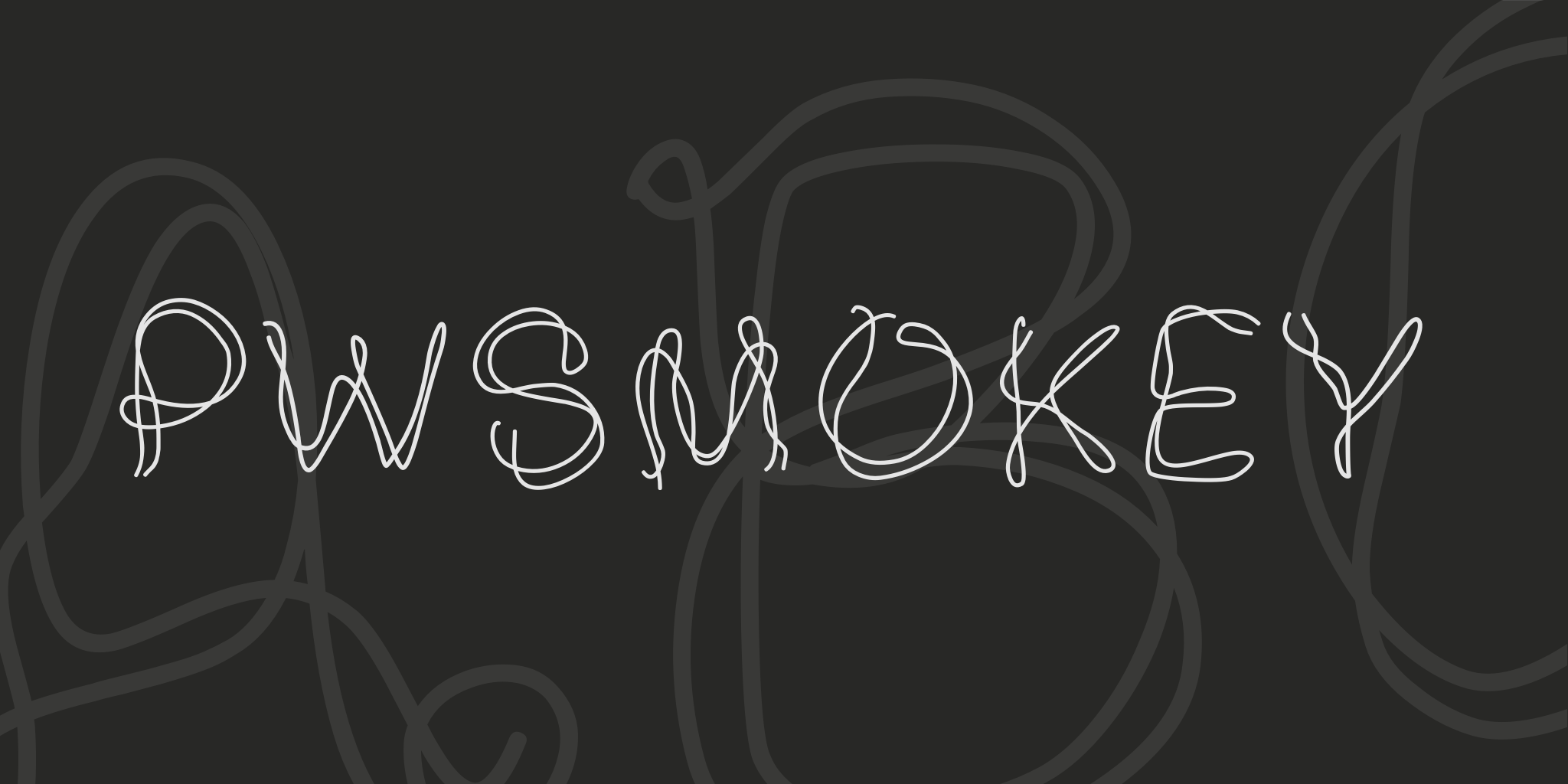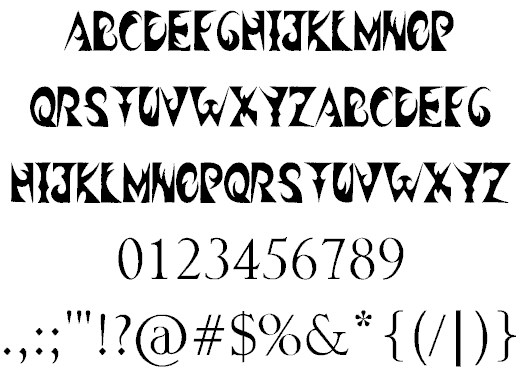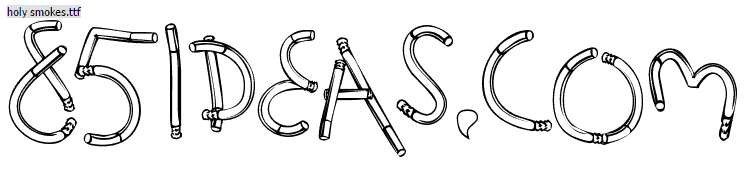
12+ der besten kostenlosen Smoke-Schriftarten für Designer 2021
Veröffentlicht: 2015-12-18Designer sollten sich darauf einstellen, diese Rauchschriftarten in ihren nächsten kreativen Grafikdesignprojekten wie Websites, Logos, Flyern, Postern und vielem mehr zu verwenden. Eines der wichtigsten Dinge, die Sie tun sollten, ist, sich auf die Anzahl der Websites mit den besten kostenlosen Smoke-Fonts zu konzentrieren. Wir haben für jedes Designprojekt eine Liste mit über 12 kostenlosen Smoke-Fonts zusammengestellt. Wir haben dies getan, um Ihre Mühe und Zeit zu sparen. Einige der kostenlosen Smoke-Fonts in dieser Liste können kostenlos heruntergeladen werden, während andere kostenpflichtig sind. Sie müssen nur eine kleine Spende leisten, um die kostenlosen Smoke-Fonts kommerziell nutzen zu dürfen. Wir sind zuversichtlich, dass Ihnen auch die besten kostenlosen arabischen Schriftarten gefallen werden.
Schriftarten mit rauchigen Effekten werden nie aus der Mode kommen, sie wurden immer wieder von Designern verwendet, um ihren Projekten Pep zu verleihen. Rauchschriftarten sind interessant und haben eine gewisse Kühnheit, die Menschen zum Text hinzieht. Egal wie attraktiv die anderen Elemente sind, diese Rauchschriftarten werden die Aufmerksamkeit des Betrachters auf den gewünschten Bereich lenken. Diese Schriftarten verleihen dem Inhalt die dringend benötigte Einzigartigkeit und helfen Ihnen, die Vielfalt Ihrer Designs zu präsentieren, insbesondere wenn sie mit Beautiful Winter and Christmas Wallpaper For Your Desktop integriert sind.
Warum die besten kostenlosen Smoke-Fonts verwenden
Im Laufe der Jahre haben Designer Rauchschriften in ihren Projekten verwendet, um ihnen ein attraktives und mutiges Aussehen zu verleihen. Die kostenlosen Smoke-Fonts wurden in den Dark-Design-Projekten ausgiebig genutzt. Unabhängig davon, ob das Design starke visuelle Grafiken enthält, erleichtern Rauchschriften es Ihnen, Ihre Botschaft an Ihr gesamtes Publikum weiterzugeben. Sind Sie ein kreativer Designer, der nach dem besten Weg sucht, beeindruckende Produkte zu bauen, suchen Sie nicht mehr! Die Rauchschrift lässt Ihren Text und Ihre Titel fetter und einzigartiger aussehen. Sie können diese auch in die besten kostenlosen Cowboy-Schriftarten für das Design von Westerntiteln integrieren.
Smoke Fonts können in Titeln, Überschriften, Logos, Postern, T-Shirts, Grafikdesign, Websites, Print und in persönlichen Projekten verwendet werden. Für einen Designer ist es schwierig, unter den vielen im Internet verfügbaren Schriftarten eine gute Smoke-Schriftart zu finden, insbesondere wenn sie nach einer kostenlosen Schriftart suchen. Ich habe versucht, ihre Aufgabe zu erleichtern, indem ich eine Liste mit über 12 kostenlosen Smoke-Fonts für Designer zusammengestellt habe. Einige der Schriftarten sind nur für den persönlichen Gebrauch kostenlos. Bitte überprüfen Sie die Lizenzvereinbarung, bevor Sie eine der Smoke-Schriftarten in Ihrem kommerziellen Projekt verwenden.
Verdampfte BB-Smoke-Schriftart
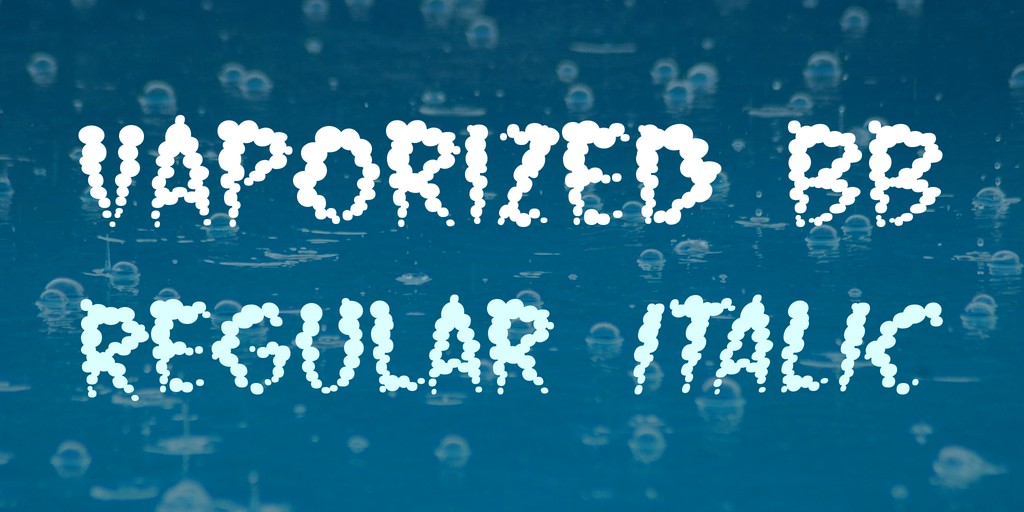
Vaporized BB Font wurde von Nate Piekos entworfen, die Rauchschrift ist wunderschön und in normaler und kursiver Schrift erhältlich. Die Buchstaben wirken verzerrt und verzerrt, die rauchende Schrift kommt auch mit Soundeffekten daher. Die Schriftart eignet sich hervorragend für jedes Projekt, das Rauch- oder Wolkeneffekte und knisternde Energiestrahlen erfordert.
Pucha-Rauch-Telegraph
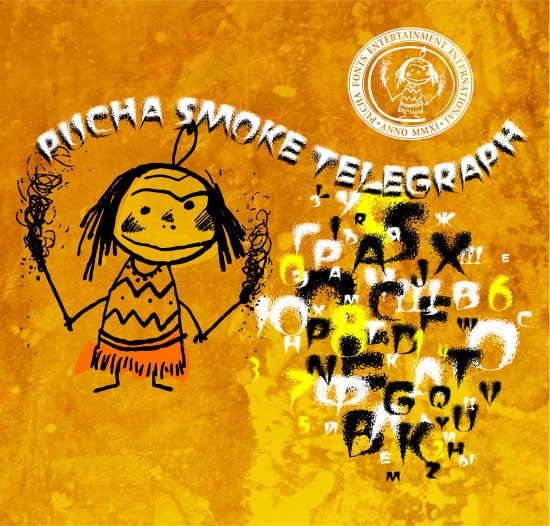
Die Schriftart Pucha Smoke Telegraph ist ziemlich fett und wird die Aufmerksamkeit des Lesers sofort auf den Text lenken. Diese Schriftart kann verwendet werden, wenn Sie eine starke Botschaft vermitteln möchten. Der Schriftsatz enthält Großbuchstaben, Kleinbuchstaben, gängige Symbole und Zahlen. Die Rauchschrift ist sowohl für den persönlichen als auch für den kommerziellen Gebrauch verfügbar. Es geht Hand in Hand mit den Free Asphalt Textures for Designers.
Alpha-Rauch
Alpha Smoke ist eine lustige Rauchschrift mit einem Rauchwolkeneffekt auf allen Alphabeten. Es ist eine coole rauchende Schriftart, mit der Sie Ihre Botschaft anzeigen können. Sie kann auch auf Postern, Websites oder praktisch überall verwendet werden, wo Sie möchten. Der Schriftsatz umfasst Großbuchstaben, Kleinbuchstaben, einige Symbole und Zahlen.
Alte Träume Schriftart
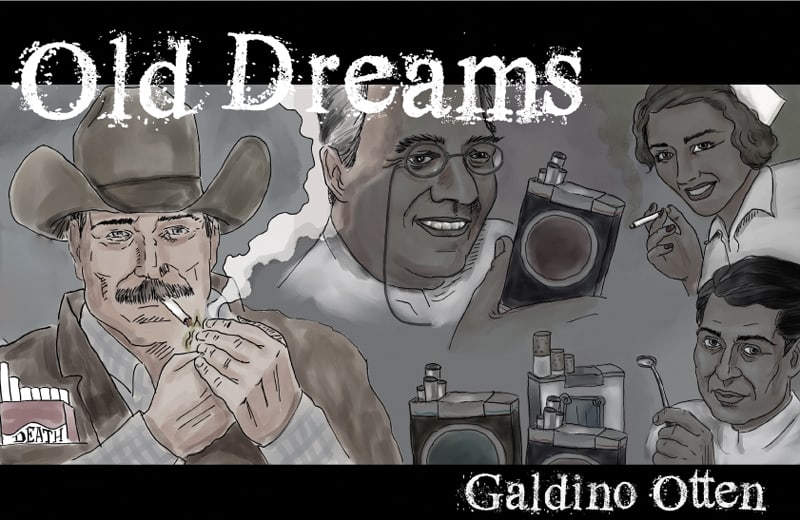
Old Dreams Font wurde von Galdino Otten entworfen; es ist eine serifenrauchende schrift mit staubigem effekt. Die Buchstaben und Symbole der Schriftart haben einen Grunge- und Sand-Look. Die Schriftart ist ideal für Schlagzeilen, Druck, Poster oder jedes Ihrer Designprojekte. Die Rauchschrift ist für den persönlichen Gebrauch kostenlos; es enthält Großbuchstaben, Kleinbuchstaben, Symbole und Zahlen.
Nach Cheret Schriftart
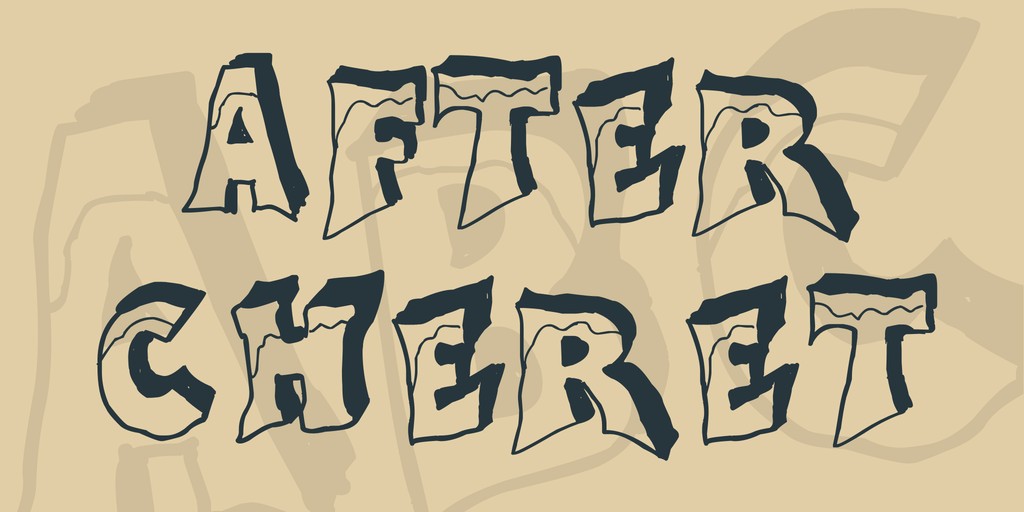
Nachdem Cheret Font eine weitere brillante Rauchschrift von Galdino Otten ist, ist es eine wunderschöne Schriftart mit klobigen Buchstaben und etwas, das wie Eis auf jedem Buchstaben oder Zeichen aussieht. Es ist eine 3D-Schriftart und hebt sich von den anderen ab. Sie kann verwendet werden, um einen bestimmten Bereich Ihres Designs, Inhalts oder Drucks hervorzuheben. Sie können diese Schriftart für Ihre persönlichen Projekte verwenden.
Tabaquera-Schriftart
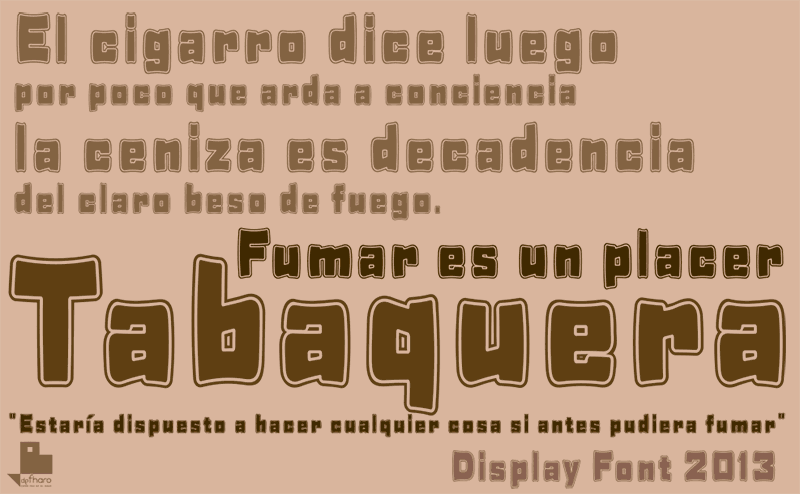
Die Tabaquera-Schrift wurde von Fernando Haro entworfen; die rauchende schrift ist eine schön konturierte, klobige, quadratische schrift mit abgerundeten ecken. Es ist eine einzigartige Rauchschrift, die jedem Ihrer Design- oder Webprojekte einen Hauch von Skurrilität und Stil verleiht. Die Schriftart Rauch hat 365 Zeichen, einschließlich Großbuchstaben, Kleinbuchstaben, Zahlen und Sonderzeichen. Die rauchende Schriftart kann sowohl für persönliche als auch für kommerzielle Projekte verwendet werden. Sie sollten auch daran denken, sich die hochauflösenden Windows 10-Hintergründe für Ihren Desktop anzusehen.
Einpacken